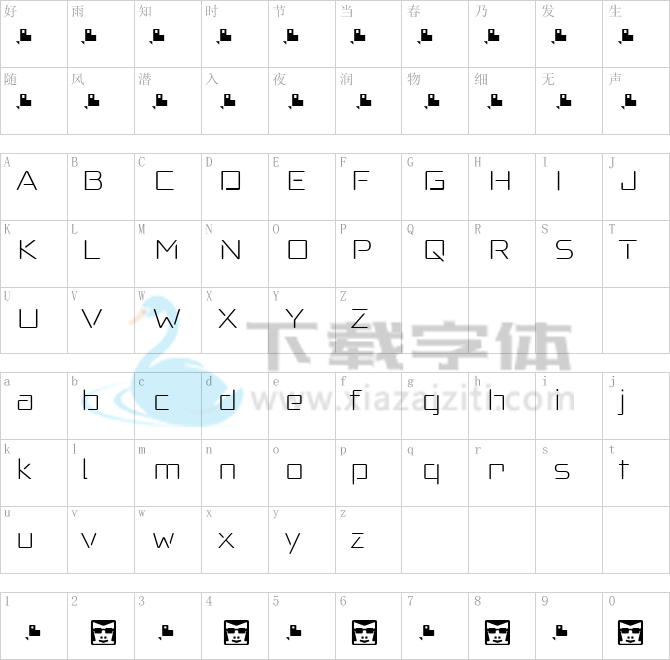
Anoxic Light.ttf字体下载,这款字体结构工整、笔画清晰,兼顾美观与易读性,适用于标题、正文、海报、包装、LOGO 等多种场景。字形优雅稳定,风格百搭耐看,适配日常排版与创意设计,让文字呈现更舒适、更具质感。Anoxic Light.ttf字体下载一笔一画,皆是细节,以均衡的比例、流畅的线条打造舒适视觉体验,字形端正大气,风格简约现代。无论是商业设计、品牌宣传还是日常排版,都能轻松驾驭,让文字更有格调与力量。Anoxic Light.ttf字体下载字体下载。